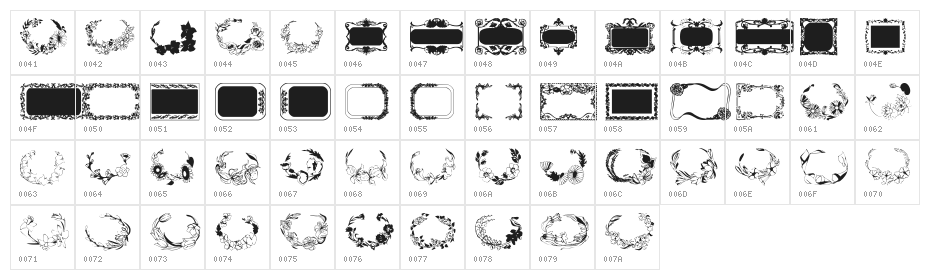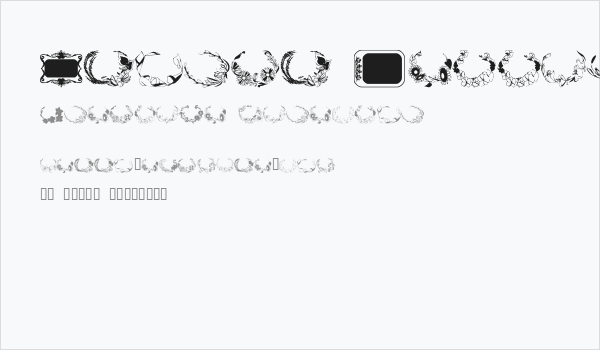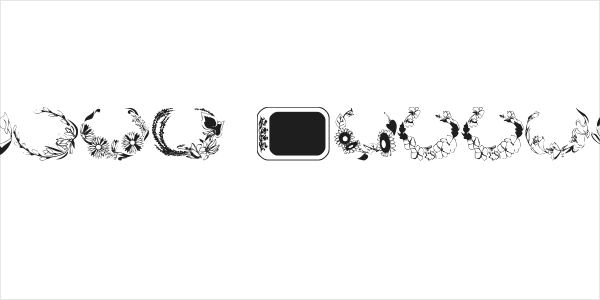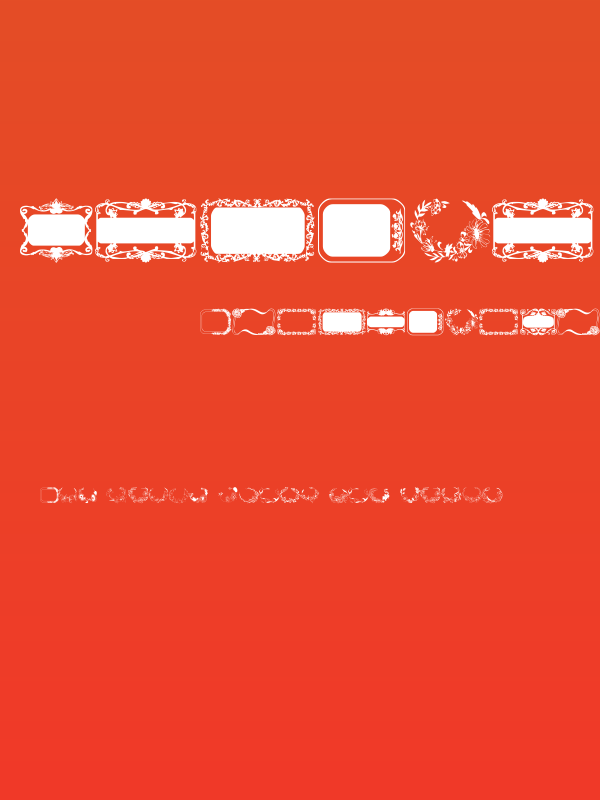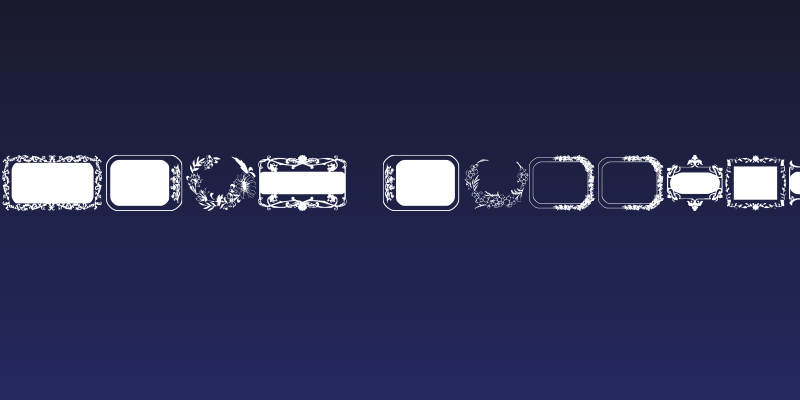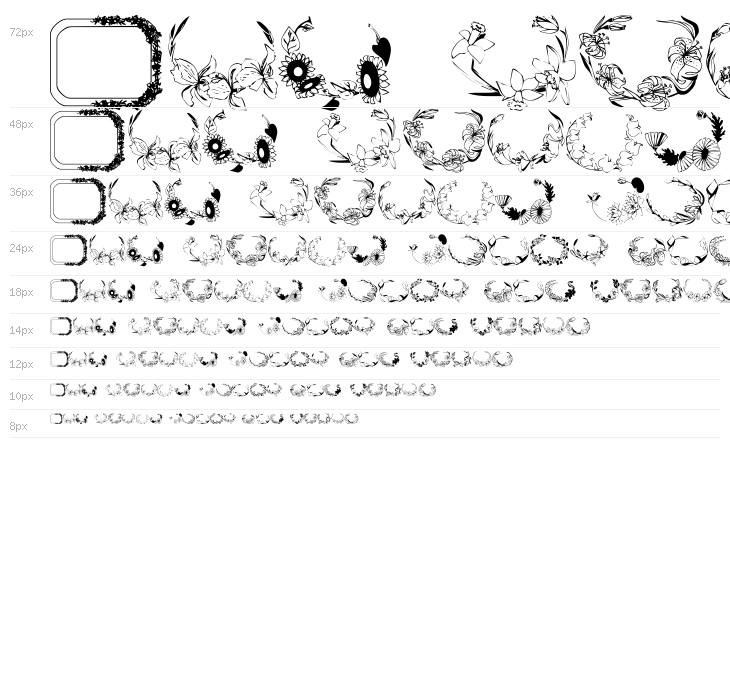
Floral Settings Font
| Stile generale | Decorative, Ornate, Botanical |
| Caso d'uso | Decorative initials, monograms, borders, and frames for special occasions. |
| Progetti proposti | Wedding invitations, greeting cards, decorative labels, event signage, scrapbooking, branding for florists or botanical shops. |